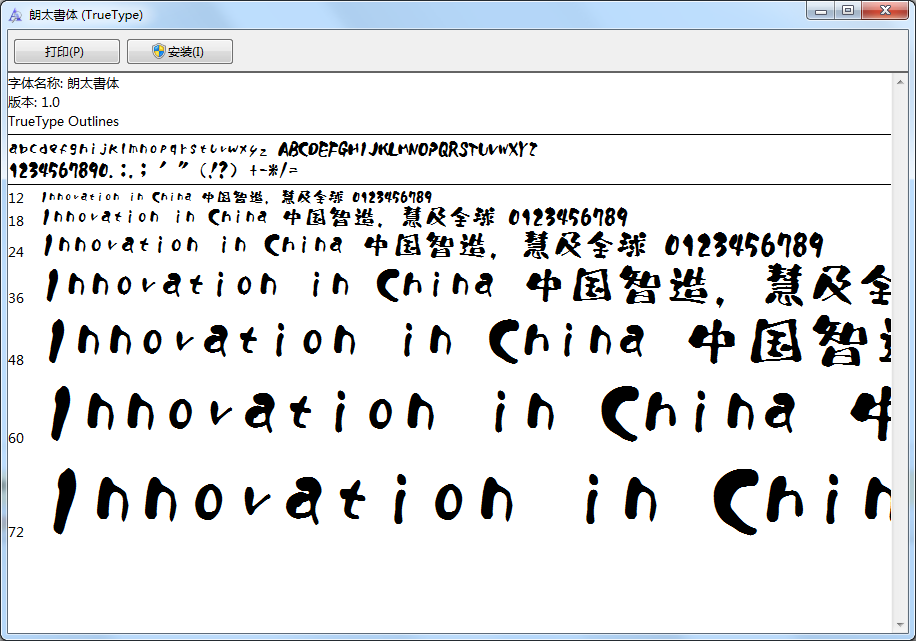
日本朗太書(shū)體字體是一款將非常大氣的字體,支持中文、英文和阿拉伯?dāng)?shù)字,筆法非常的強(qiáng)勁有力,字體也特別的粗,非常的醒目,可適用于做宣傳用字,喜愛(ài)的朋友趕快到綠色資源網(wǎng)下載體驗(yàn)吧!
朗太書(shū)體字體是一款手寫(xiě)體書(shū)法字體,字體大氣雄厚,本作品可用于廣告設(shè)計(jì)字體、網(wǎng)頁(yè)設(shè)計(jì)字體、包裝設(shè)計(jì)字體、 屏幕顯示字體等。